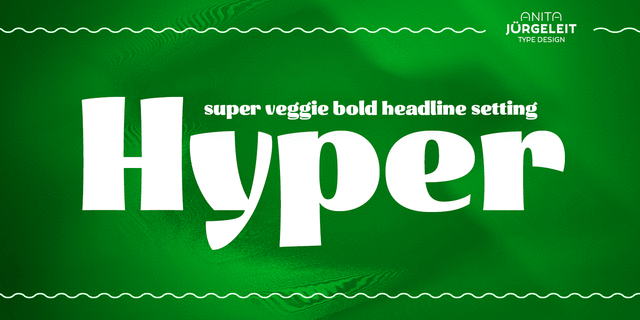
Hyper – это максимально заголовочный шрифт для фруктов, овощей, цветов и всех красивых и здоровых вещей, которые наполняют вашу жизнь радостью и удовольствием. Hyper выглядит лучше всего на больших и даже огромных размерах. Поэтому, для тонкой настройки дизайна, Hyper отображается в двух основных начертаниях: Hyper Black создан для заголовков и логотипов. Hyper Grande сделан для очень больших надписей на плакатах или больших баннерах. Оно имеет немного больше элегантности за счет более тонких горизонтальных штрихов. Хорошо сформированные буквы Hyper рифмуются друг с другом, как-будто держатся за руки.
Особое внимание уделяется букве f, которая адаптирует свою форму, чтобы заключить следующую букву в уютное объятие. Для этого сделаны 62 специальные F-лигатуры, которые управляются open-type фачами.
Hyper поддерживает все необходимые функции: минускульные цифры, под и надстрочные индексы, дроби, числители и знаменатели, много лигатур.
Шрифт разработала Анита Юргелайт в 2019 году.